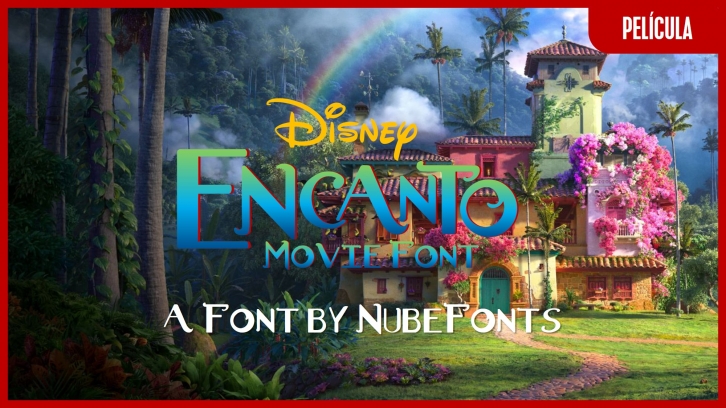
Free download of Disney Encanto Font. Released in 2022 by NubeFonts and licensed for personal-use only. Click now to create a custom image with your own words that you can download.
La fuente está basada en su logotipo, la fuente fue recreada por NubeFonts a partir del alfabeto que se compro en la página ETSY gracias a que tenÃamos dinero en PayPal